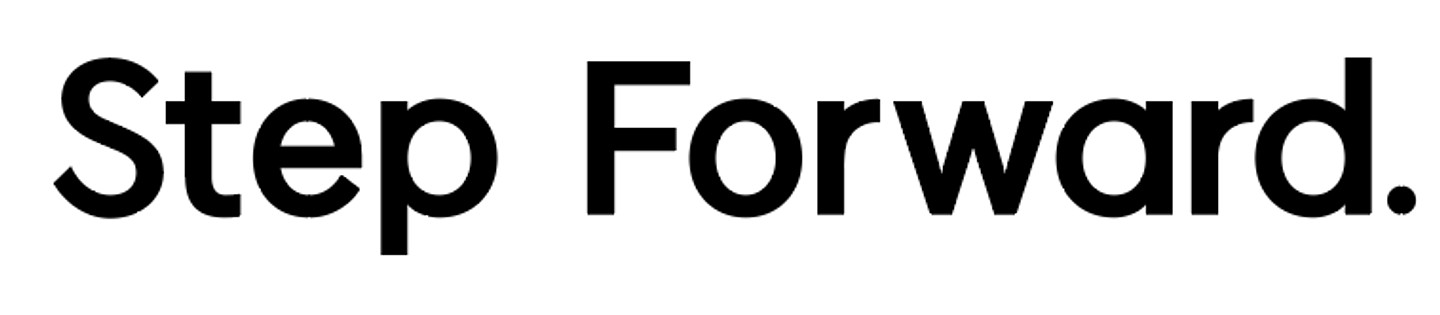
제가 예전에 로고 작업하면서 사용했던 폰트인데 폰트가 날아갔는지 도무지 찾을 수가 없네요 ㅠㅠ 혹시 아시는 분 계실까요?
이 폰트 HU하늘고딕 140로 알려주셨는데 느낌은 비슷하지만 히읗이 다르고 사진 속 폰트가 획이 더 긴 느낌이라 정확히 알려주실분 ㅜㅜ
헤이세이노트손글씨라고 써져있는데, 검색해도 나오질 않아서요. 무슨 폰트일까요? 제일 비슷한 일본어 폰트라도 알고 싶습니다.